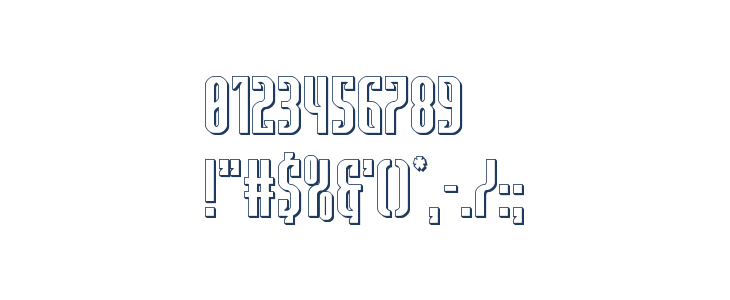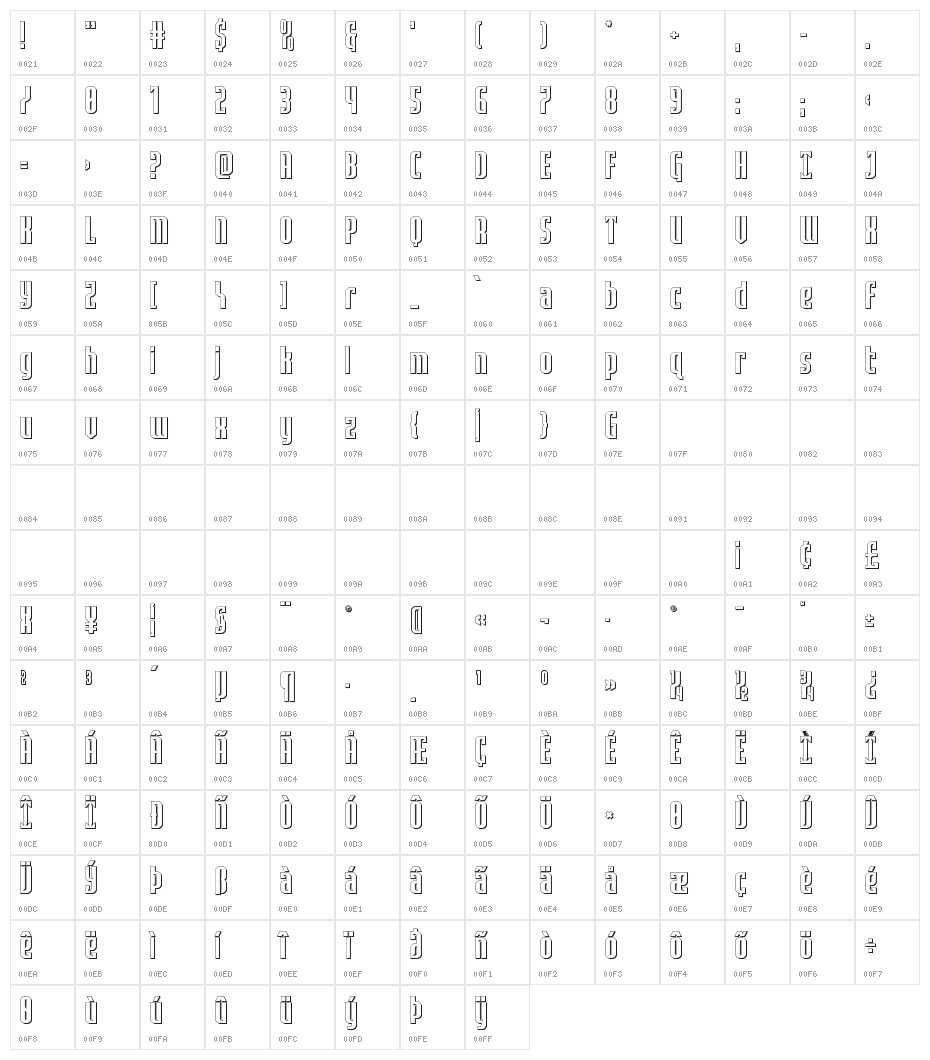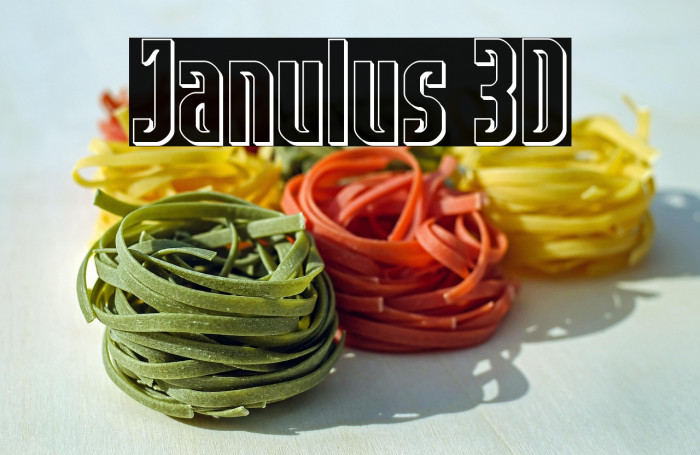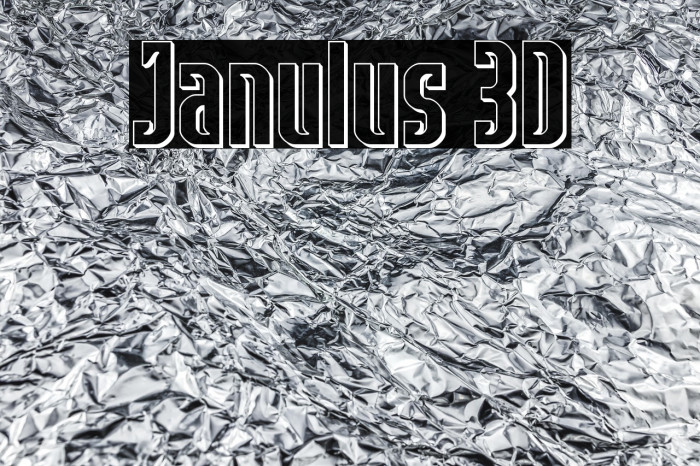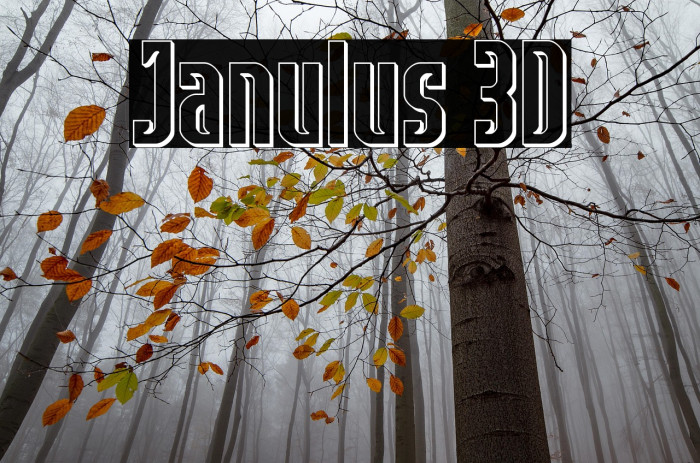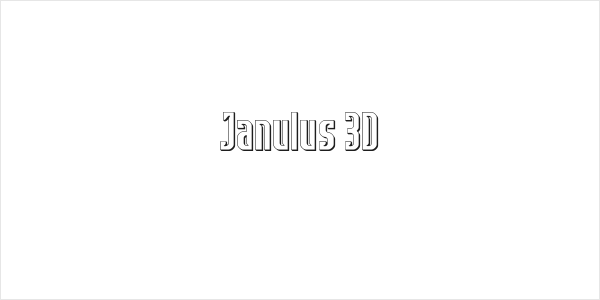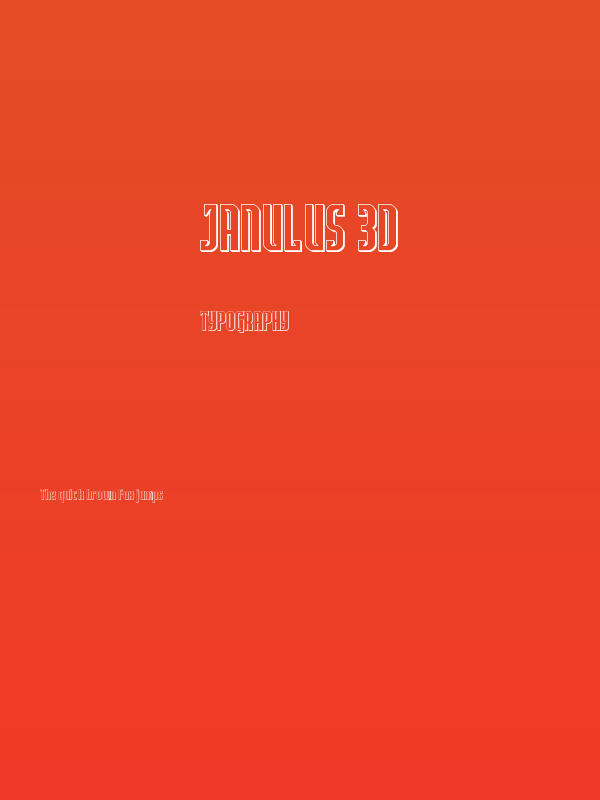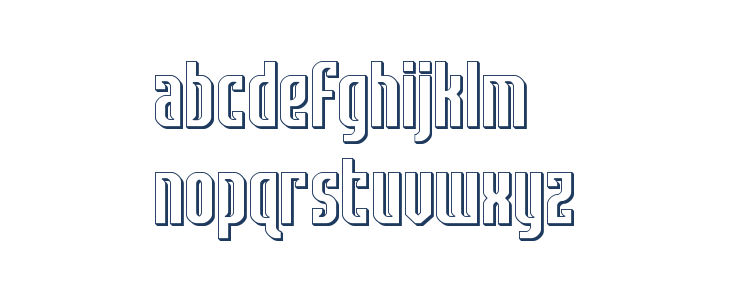
Janulus 3D Font
| Projetos propostos | Ideal for poster designs, video game graphics, futuristic branding, and any project requiring a standout, modern typeface. |
Janulus 3D